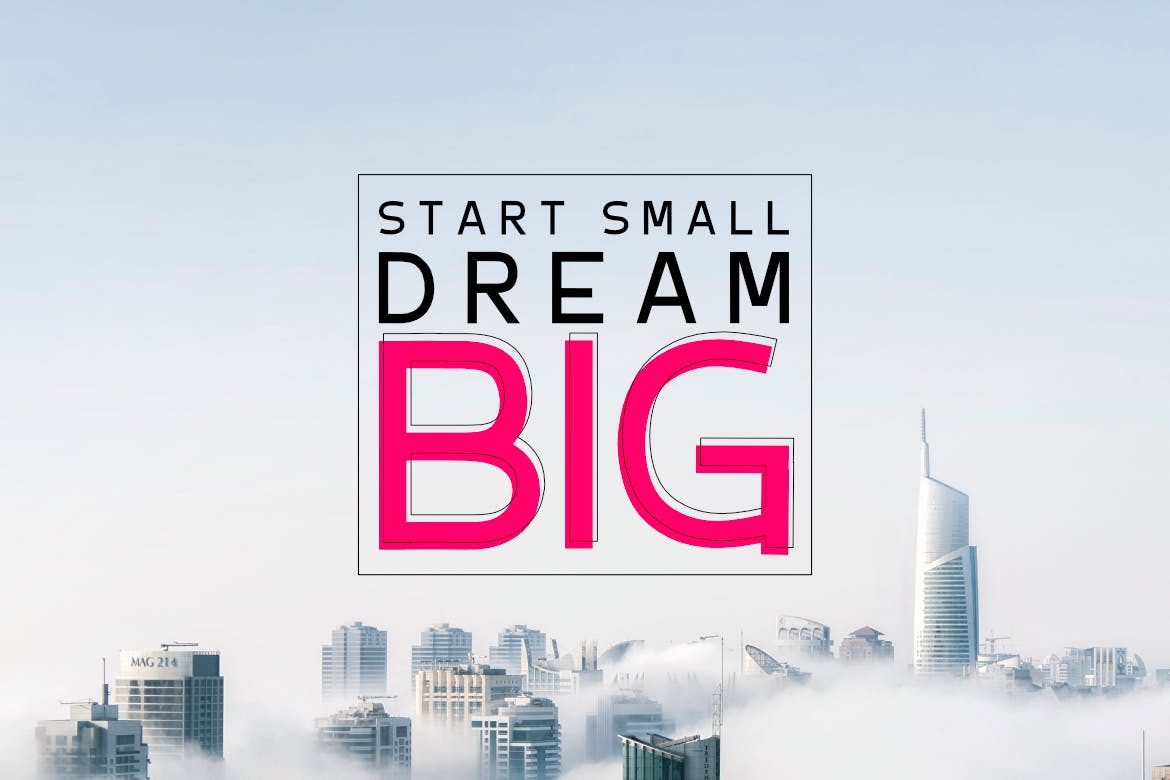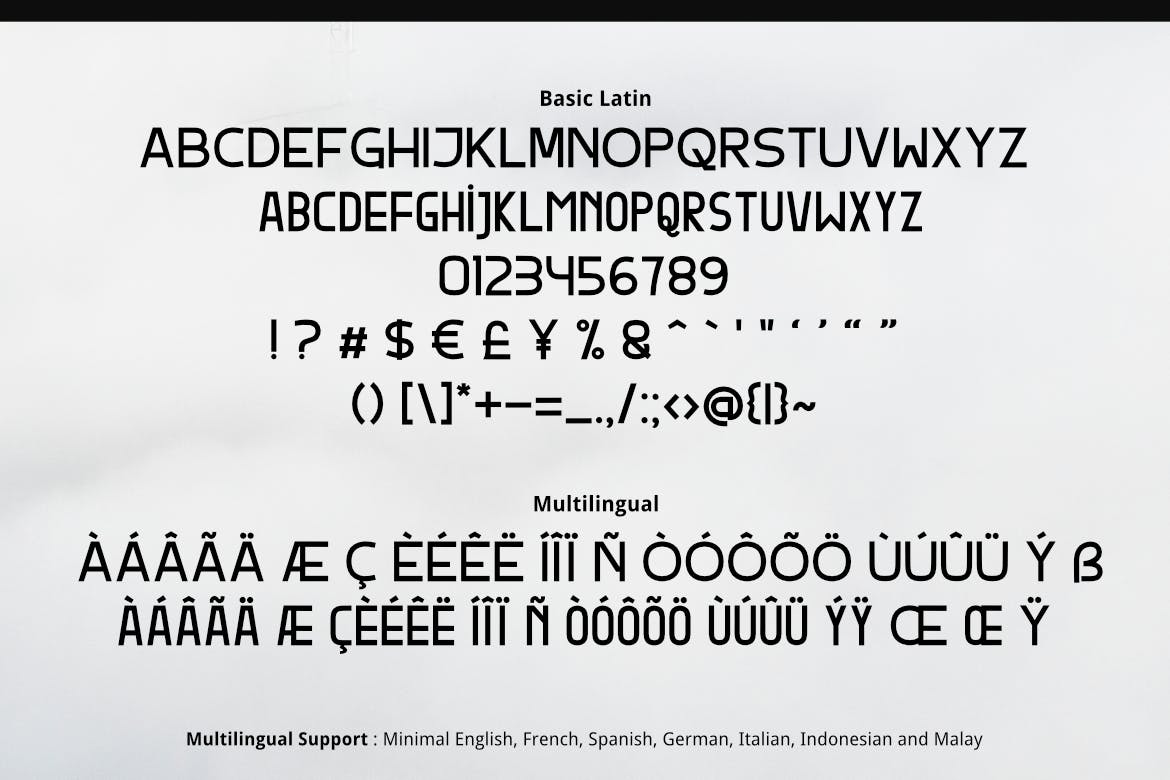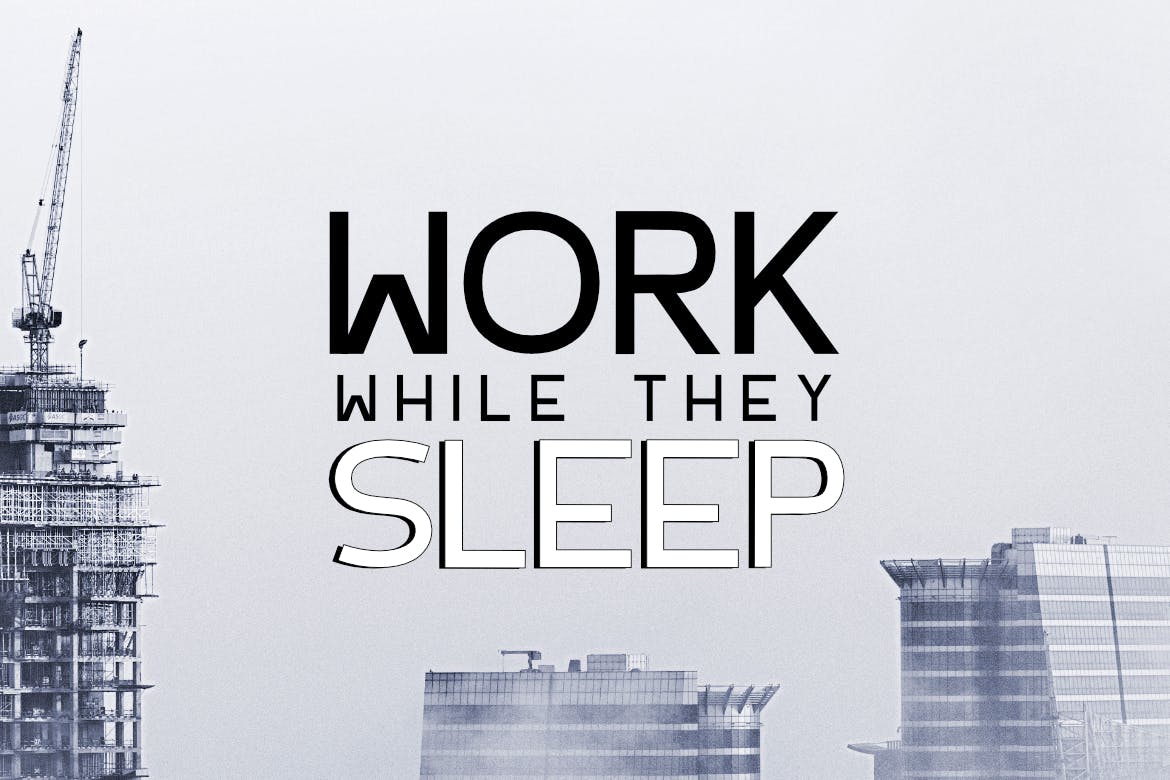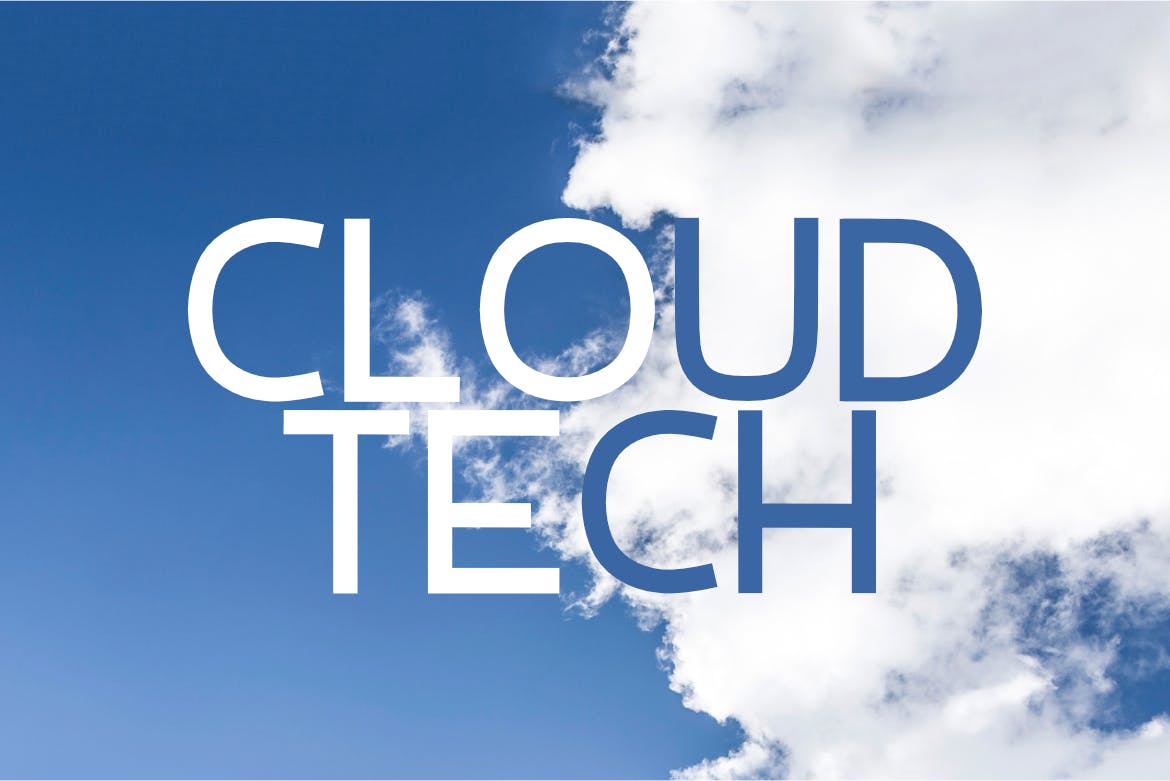
فونت Wagon
فونت Wagon یک فونت چندمنظوره و مدرن است که برای پروژههای مختلفی مانند کتابهای کودک، نقل قولها، لوگو، عناوین و تیترها مناسب است.
پشتیبانی از زبانهای پایه (کاراکترها، اعداد و نمادهای استاندارد انگلیسی) و چندزبانه (حداقل انگلیسی، فرانسوی، اسپانیایی، آلمانی، ایتالیایی، اندونزیایی، مالایی)